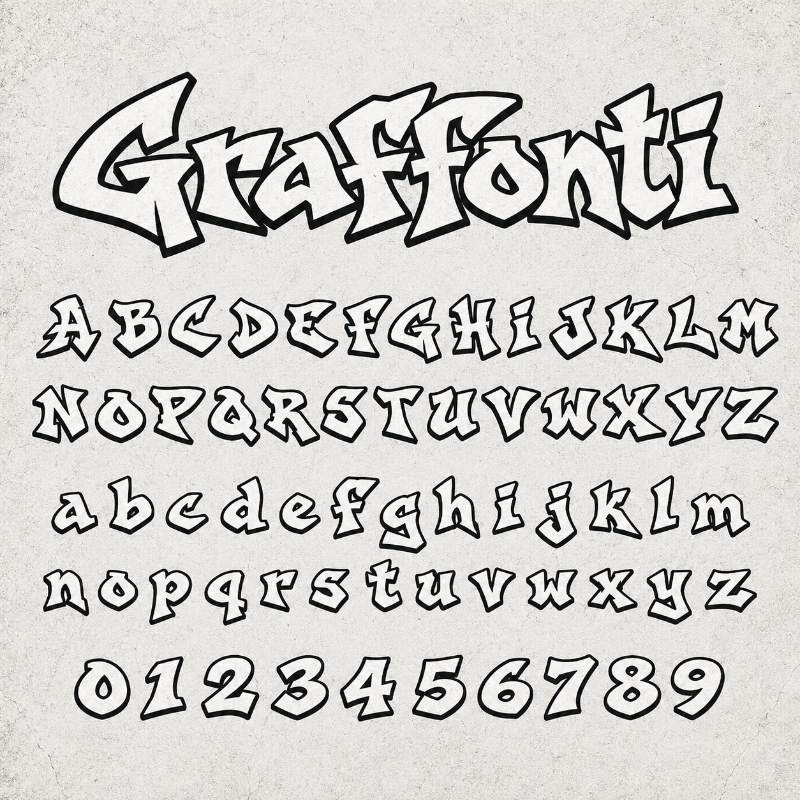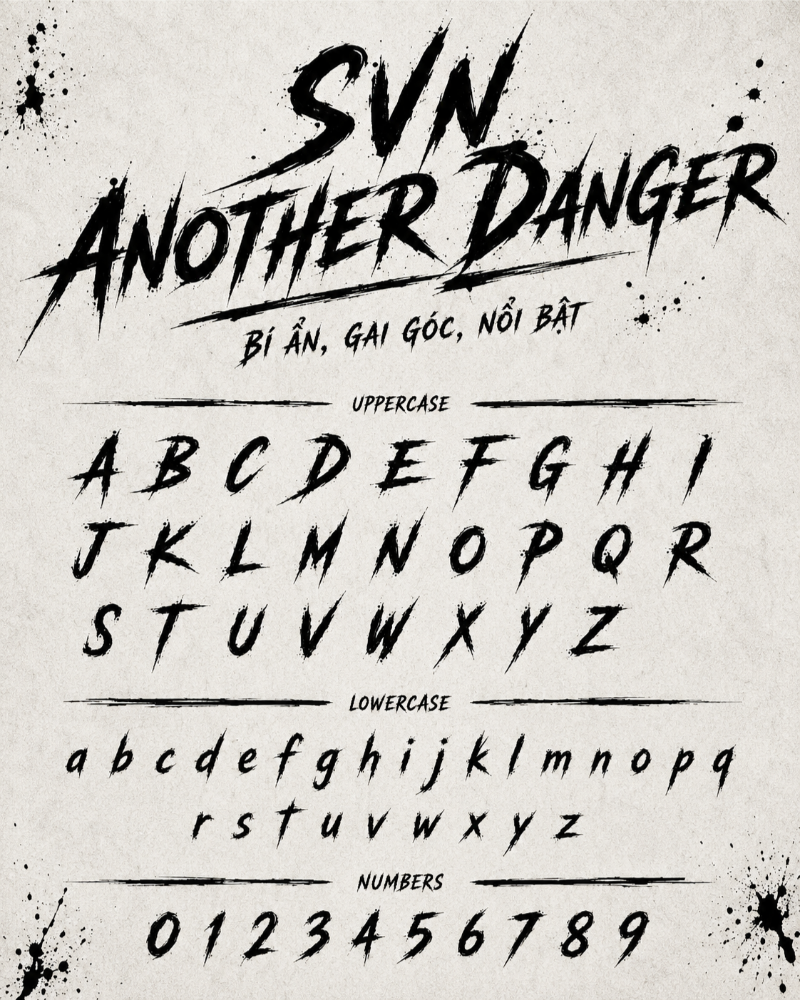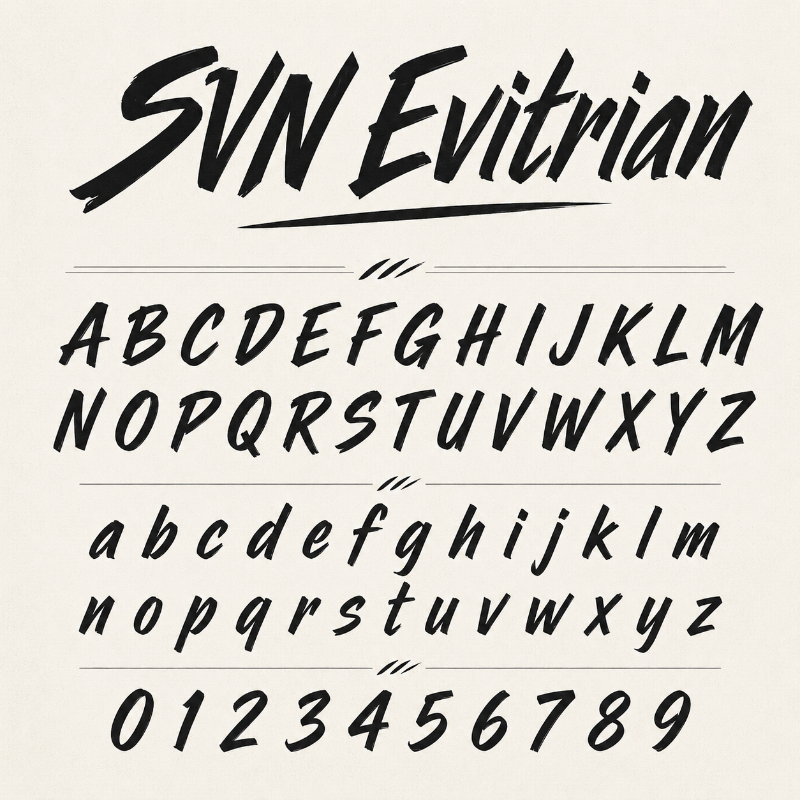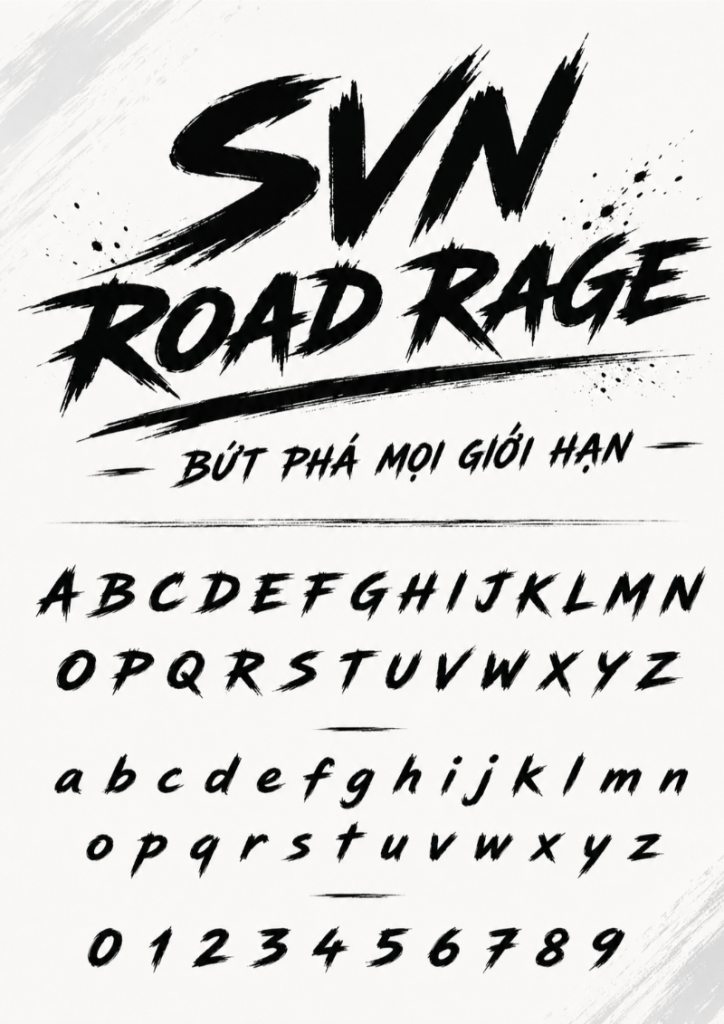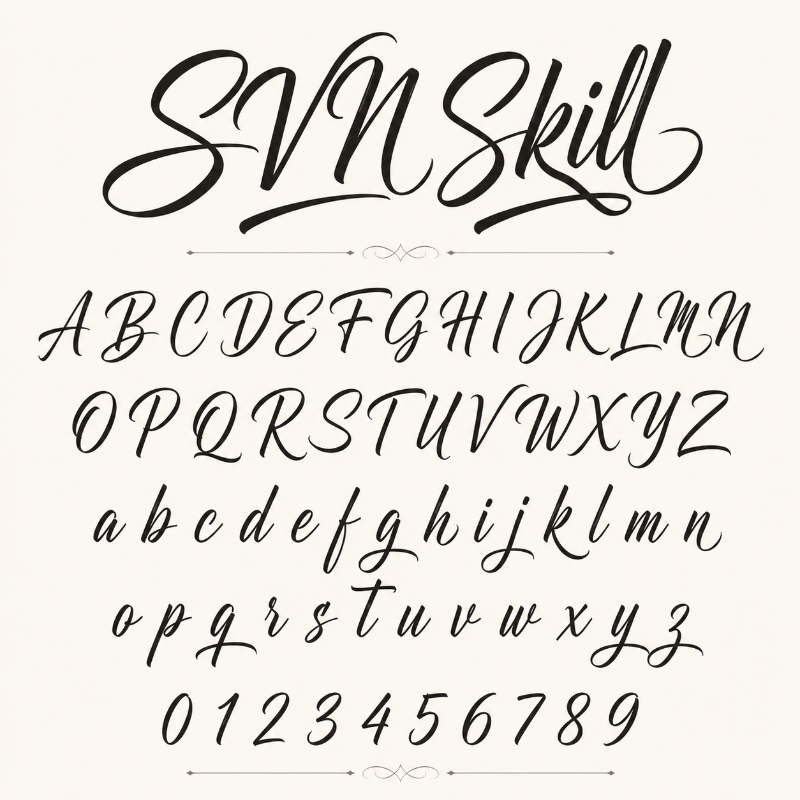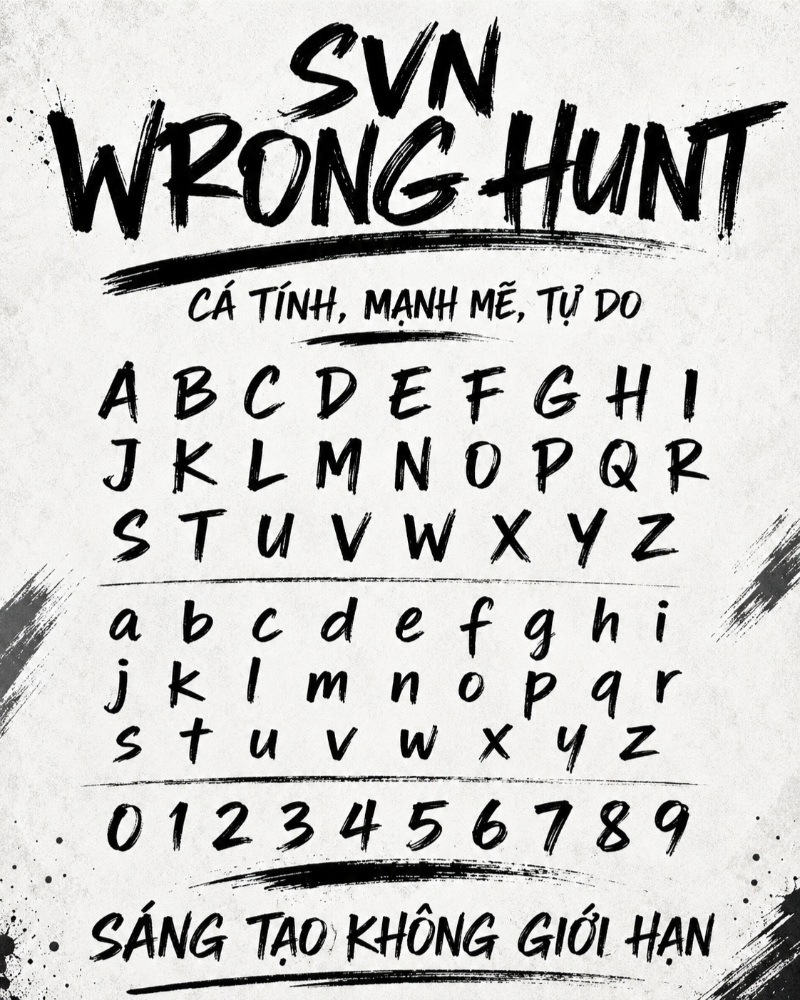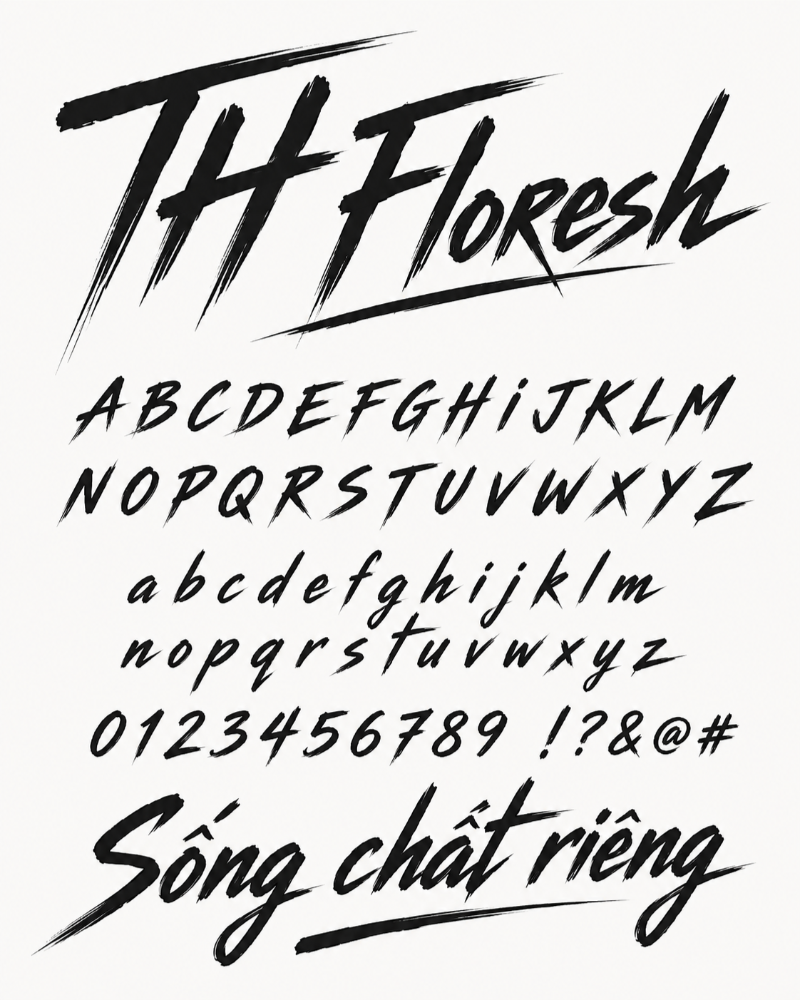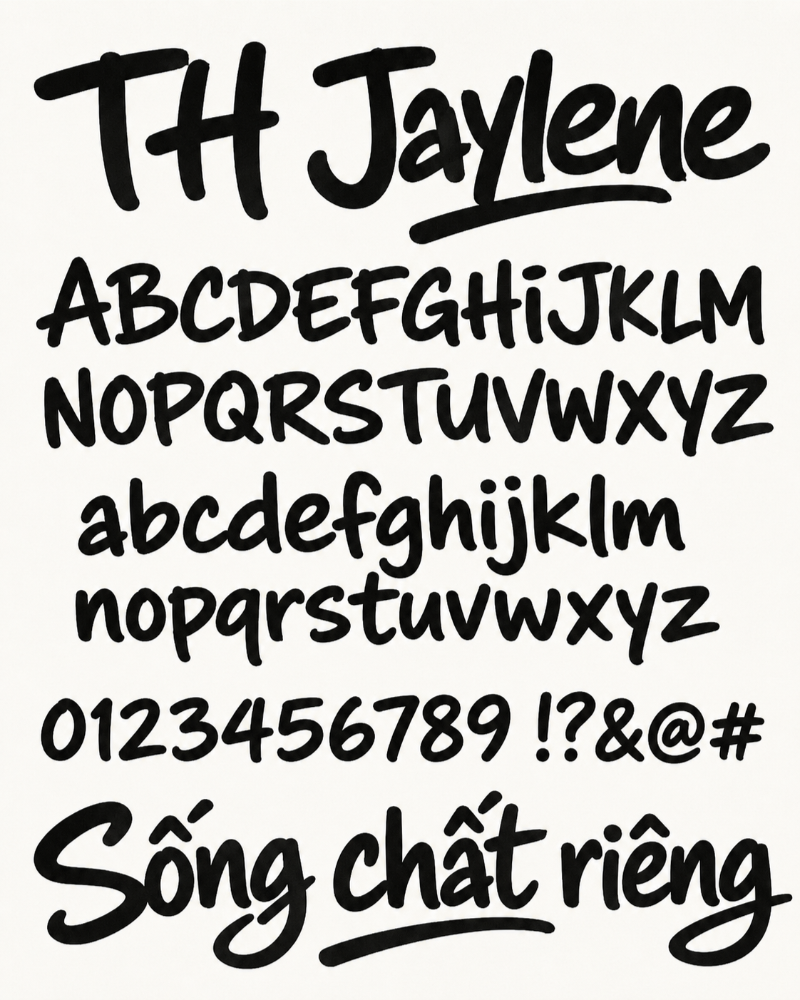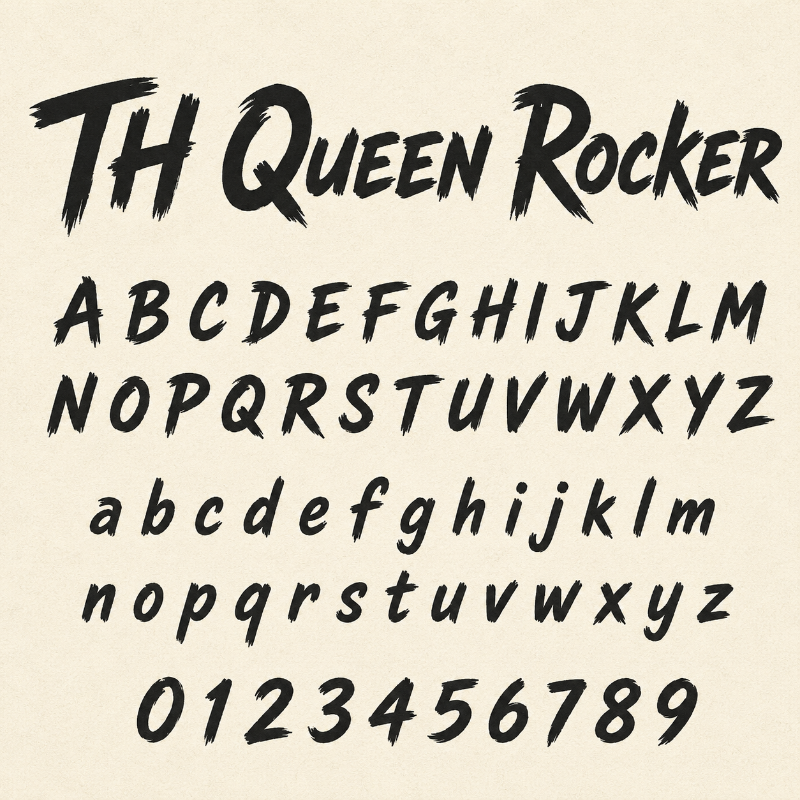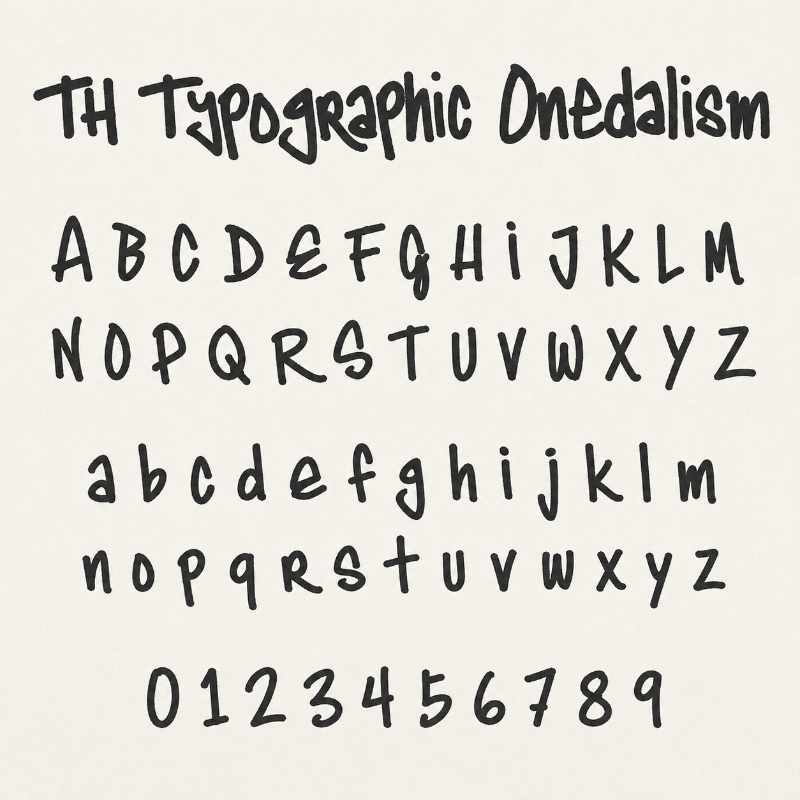
Chia sẻ 10+ Font Graffiti việt hóa đẹp miễn phí cho Designer
Xu hướng thiết kế mang hơi thở đường phố như streetwear, underground và hiphop đang ngày càng được ưa chuộng trong nhiều ấn phẩm sáng tạo. Sự pha trộn giữa văn hóa đô thị, cá tính nổi loạn và nghệ thuật thị giác giúp các thiết kế trở nên nổi bật, mạnh mẽ và giàu dấu ấn riêng. Tuy nhiên, với nhiều designer, việc tìm được một font chữ graffiti đủ “chất”, có nét bụi bặm đúng tinh thần đường phố và vẫn hỗ trợ tiếng Việt đầy đủ dấu luôn là bài toán không hề đơn giản.
Trong bài viết này, chúng tôi đã tổng hợp và chọn lọc hơn 10 font graffiti việt hóa đẹp, cá tính và dễ ứng dụng. Bộ font này sẽ giúp bạn rút ngắn thời gian tìm kiếm, hạn chế lỗi hiển thị tiếng Việt và tự tin sử dụng cho nhiều dự án thiết kế như áo thun, poster, banner, bìa nhạc, bao bì sản phẩm hay các ấn phẩm truyền thông mang phong cách street style.
Các phong cách Font graffiti phổ biến designer nên nắm rõ
Graffiti không bị giới hạn trong một kiểu chữ cố định. Mỗi phong cách graffiti mang một tinh thần riêng, phù hợp với từng mục đích thiết kế khác nhau. Vì vậy, để chọn đúng font chữ cho poster, áo thun, logo hay ấn phẩm truyền thông, designer cần hiểu rõ những nhóm phong cách cơ bản dưới đây.
Font Graffiti việt hóa
• Tagging: là kiểu chữ mô phỏng nét ký tên nhanh, thường có đường nét mảnh, tự do và giàu tính ngẫu hứng. Phong cách này phù hợp để dùng làm chữ ký nhỏ trên poster, điểm nhấn trong artwork hoặc logo cho các thương hiệu cá nhân có cá tính mạnh, nổi loạn và khác biệt.
• Throw-up: hay còn gọi là Bubble, nổi bật với dáng chữ tròn, phồng, dày và có viền rõ ràng. Kiểu font này tạo cảm giác vui nhộn, trẻ trung và dễ nhận diện. Đây là lựa chọn rất hợp cho thiết kế áo thun streetwear, sticker, bao bì sản phẩm sáng tạo hoặc các ấn phẩm hướng đến giới trẻ.
• Wildstyle: là phong cách graffiti có cấu trúc phức tạp, chữ cái thường góc cạnh, đan xen và liên kết chặt với nhau. Do độ nhận diện chữ không quá cao, Wildstyle thường được dùng như một yếu tố trang trí nền, điểm nhấn thị giác hoặc để tạo cảm giác mạnh mẽ, phá cách cho tổng thể thiết kế.
• Brush / Marker: mô phỏng hiệu ứng nét cọ, bút marker, vệt sơn khô, nét xước hoặc sơn chảy. Phong cách này thường được dùng cho tiêu đề chính, poster sự kiện âm nhạc, thiết kế mang màu sắc gai góc, kinh dị, Halloween hoặc các chủ đề cần cảm giác thô ráp, mạnh và giàu năng lượng.
10+ Font Graffiti việt hóa đẹp, dễ ứng dụng
Để bạn dễ chọn font phù hợp với từng kiểu thiết kế, danh sách dưới đây được sắp xếp theo các phong cách graffiti phổ biến, từ mạnh mẽ, đường phố đến kinh dị và cá tính.
SVN Road Rage
SVN Road Rage gây ấn tượng với dáng chữ to, góc cạnh và đầy năng lượng. Các vệt xước ở phần đuôi chữ tạo cảm giác chuyển động mạnh, rất hợp với thiết kế về tốc độ, xe cộ, thể thao mạo hiểm hoặc poster hành động.
Font chữ SVN Road Rage
SVN Wrong Hunt
SVN Wrong Hunt tái hiện rõ nét cảm giác chữ được phun trực tiếp bằng sơn xịt lên tường. Font này mang đậm tinh thần hiphop, street art và văn hóa đường phố. Đây là lựa chọn phù hợp cho poster âm nhạc, thời trang streetwear, bìa album hoặc các thiết kế cần sự tự do, phóng khoáng và nổi loạn.
SVN Another Danger
SVN Another Danger kết hợp giữa chất graffiti bụi bặm và cảm giác rùng rợn của phong cách kinh dị. Đường nét chữ mạnh, gai góc, tạo hiệu ứng thị giác khá dữ dội. Font này rất hợp cho ấn phẩm Halloween, poster nhạc rock, metal, game kinh dị hoặc các thiết kế cần không khí u tối, bí ẩn.
TH Floresh
TH Floresh sở hữu nét chữ mảnh nhưng chắc, có độ sắc và nhịp điệu rõ ràng. Font mang lại cảm giác nhanh, gọn, kịch tính và hơi hướng hành động. Bạn có thể dùng TH Floresh cho poster cá tính, banner sự kiện, thiết kế thời trang hoặc các sản phẩm cần tạo điểm nhấn mạnh mà không quá nặng nề.
TH Jaylene
TH Jaylene nổi bật với dáng chữ dày, tròn mềm và có độ căng thị giác tốt. Phong cách này gợi cảm giác về những mảng chữ phun sơn khổ lớn thường thấy trên tường phố, hầm cầu hoặc các khu đô thị. Font rất phù hợp cho thiết kế streetwear, poster hiphop, banner sự kiện đường phố hoặc các ấn phẩm cần vẻ ngoài mạnh mẽ nhưng vẫn thân thiện.
Graffonti Việt hóa
Graffonti Việt hóa mang phong cách chữ bong bóng cổ điển, tròn trịa và dễ nhận diện. Điểm mạnh của font này là khả năng đọc tốt, không quá rối mắt như nhiều kiểu graffiti phức tạp khác. Đây là lựa chọn hợp lý cho các thiết kế trẻ trung, vui nhộn, phá cách nhưng vẫn cần truyền tải thông điệp rõ ràng, chẳng hạn như sticker, áo thun, poster học đường hoặc nội dung dành cho giới trẻ.
SVN Skill
SVN Skill sở hữu nét chữ bay bổng, uốn lượn tự nhiên nhưng không hề mềm yếu. Font vẫn giữ được tinh thần mạnh mẽ, cá tính và đậm chất đường phố. Đây là lựa chọn rất phù hợp cho thiết kế áo thun, hoodie, logo local brand hoặc các ấn phẩm thời trang trẻ.
Font chữ chất lượng luôn là trợ thủ quan trọng giúp designer tạo nên những thiết kế khác biệt. Hy vọng danh sách 10+ font graffiti Việt hóa trên đây sẽ giúp bạn có thêm nhiều lựa chọn để sáng tạo poster, áo thun streetwear, ấn phẩm underground hoặc các thiết kế mang đậm dấu ấn cá nhân.